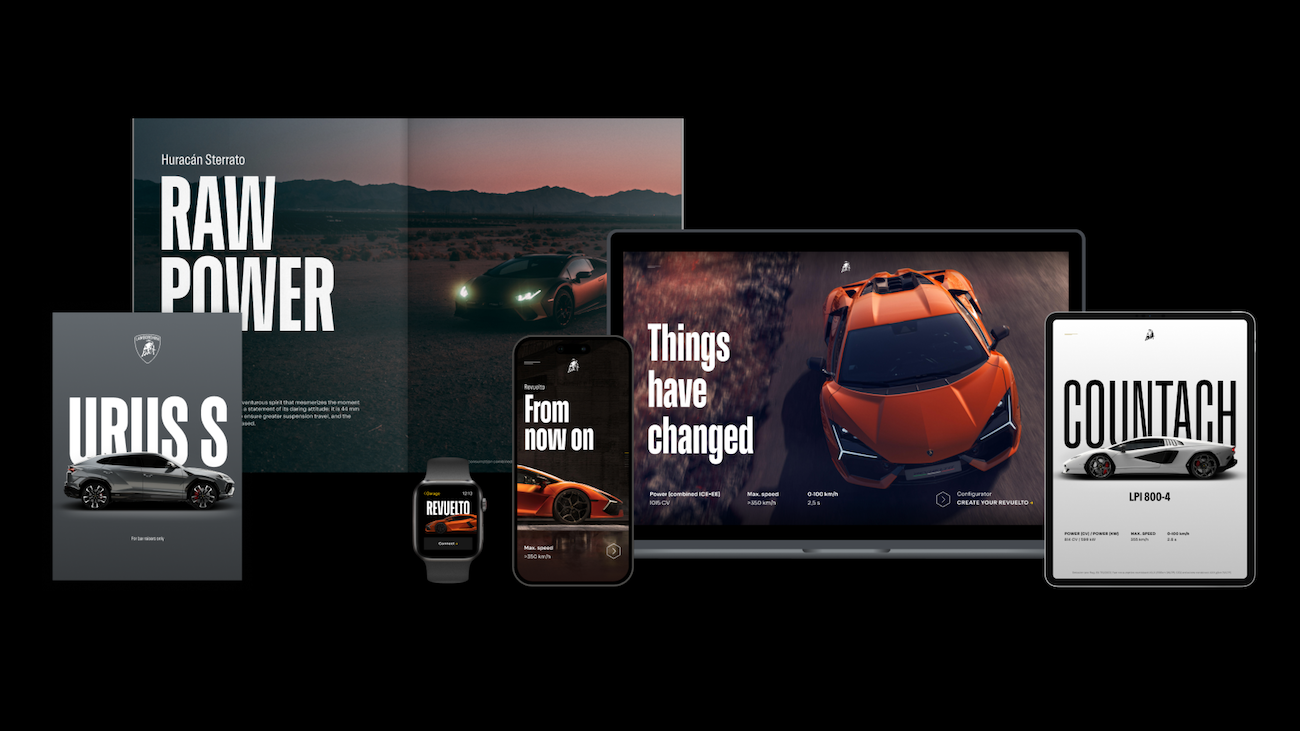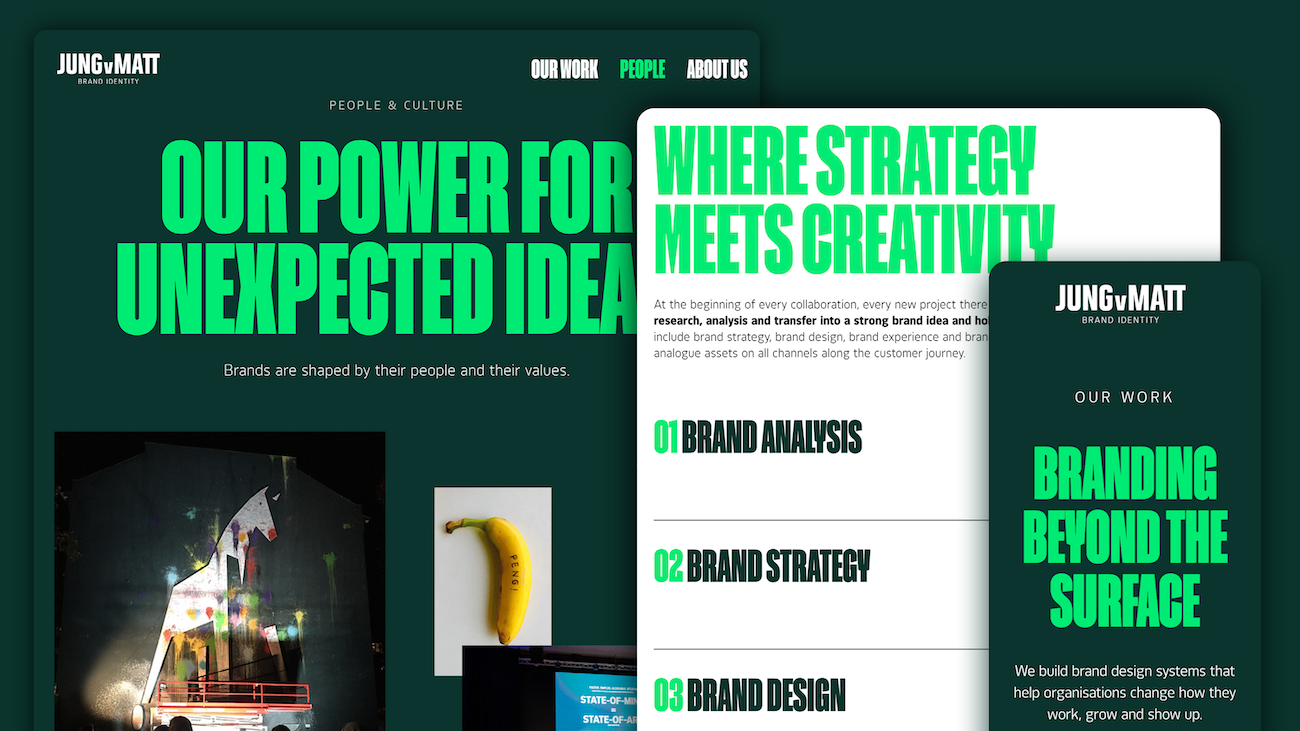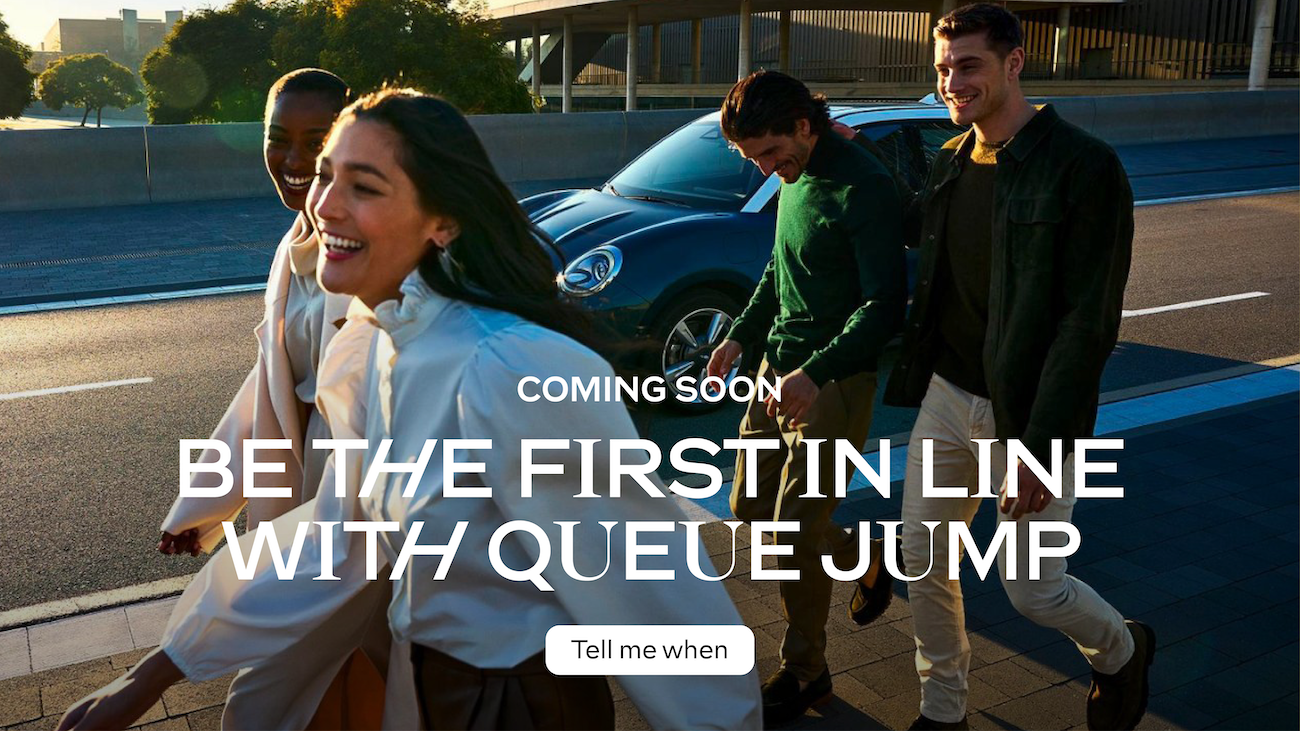
»Schrift ist nicht nur Stil, sondern Markenidentität«
Schriftgestalter Henning Skibbe über Typographic Branding und warum Marken heute stärker über Schrift sprechen müssen.
Typografie ist längst mehr als ein ästhetisches Detail – sie ist ein strategisches Werkzeug in der Markenführung. Im Gespräch erläutert Henning Skibbe, warum Schrift Haltung transportiert, Differenzierung ermöglicht und welche Rolle neue Technologien dabei spielen. Das Thema vertieft er auch in seinem Webinar »Typographic Branding«.
PAGE: Henning, warum ist Typografie heute ein strategisches Thema für Marken?
Henning Skibbe: Schrift ist weit mehr als Stilmittel. Sie ist ein zentraler Bestandteil der Markenidentität. Über Typografie kommunizieren Marken Haltung, Tonalität und Konsistenz – über alle Kanäle hinweg. In einer Zeit, in der Marken auf so vielen Plattformen gleichzeitig stattfinden, ist das unverzichtbar. Eine Marke ohne typografische Strategie wirkt beliebig. Typografie sorgt dafür, dass eine Marke auch ohne Logo erkannt wird. Sie trägt die DNA im Alltag.
Was sind aus deiner Sicht die zentralen Aspekte von Typographic Branding?
Ich betrachte Typografie – auch in meinem Webinar »Typographic Branding«– aus drei Perspektiven: strategisch, gestalterisch und technologisch. Es geht darum, wie Schriftwahl oder -entwicklung gezielt zur Markenführung beitragen kann – ob durch den Einsatz bestehender Schriftfamilien oder durch Custom Fonts. Ein Schwerpunkt liegt darauf, wie sich eine typografische Sprache definieren lässt, die Wiedererkennbarkeit und Flexibilität verbindet. Außerdem geht es um die Frage, wie typografische Entscheidungen im Designprozess fundiert begründet werden können.
Wie verändert sich Typografie aktuell durch neue Technologien wie Variable Fonts oder KI?
Technologie eröffnet enorme Freiräume. Variable Fonts ermöglichen beispielsweise, dass Marken mit Dynamik und Flexibilität arbeiten können, ohne an Konsistenz zu verlieren. Und KI kann typografische Workflows effizienter machen, etwa bei der Schriftanalyse oder bei Tests zur Lesbarkeit. Aber Technik ersetzt kein gestalterisches Denken. KI kann inspirieren, braucht jedoch eine klare Richtung – und die kommt aus der Markenstrategie.
Was sind denn aus deiner Sicht die häufigsten Fehler, die Marken in der Typografie machen?
Viele Marken unterschätzen die Rolle der Schrift oder treffen Entscheidungen zu kurzfristig – etwa aus Budgetdruck oder aufgrund von Trends. Dabei ist Typografie einer der langlebigsten Bestandteile einer visuellen Identität. Wer sie nicht strategisch entwickelt, muss später nachbessern. Ein weiterer Punkt: Accessibility und Lesbarkeit werden häufig zu spät berücksichtigt. Gute Typografie schafft nicht nur Charakter, sondern auch Zugänglichkeit – und das wird zunehmend zu einem Qualitätskriterium für Marken.
Für wen ist das Thema »Typographic Branding« besonders relevant – und warum gerade jetzt?
Relevant ist es für alle, die Marken führen oder gestalten: Designer:innen, Creative Directors, Markenstrateg:innen ebenso wie Brand Manager:innen in Unternehmen. Typografie verbindet Design, Technologie und User Experience. Und weil Marken über zahlreiche Touchpoints hinweg kommunizieren, ist typografische Konsistenz längst kein Nice-to-have mehr, sondern eine Voraussetzung für Glaubwürdigkeit. Wer Schrift strategisch versteht, verfügt über ein starkes Instrument, um Marken zukunftsfähig zu machen.
Typografie strategisch weiterdenken – mit Henning Skibbe
Henning Skibbe, einer der profiliertesten Schriftgestalter im deutschsprachigen Raum, vertieft im Webinar »Typographic Branding« die hier angesprochenen Fragen zur Rolle von Schrift in der Markenführung. Anhand von Praxisbeispielen zeigt er, wie sich typografische Systeme entwickeln und argumentativ im Markenprozess verankern lassen. Als PAGE+ Abonnent:innen erhaltet ihr auf die Teilnahme übrigens einen Rabatt von 30 Prozent.